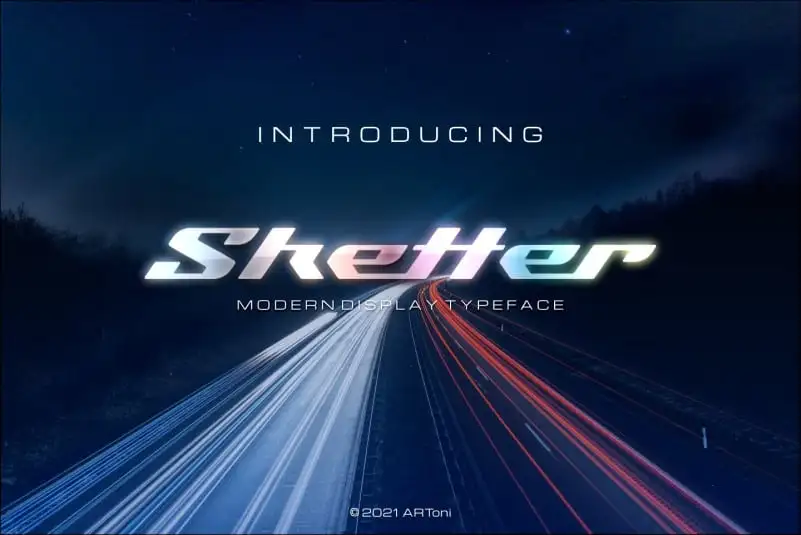
Sketter Display Font – Download Grátis
A fonte Sketter Display é uma excelente opção para projetistas que desejam criar designs chamativos e inovadores em plataformas digitais. Desenvolvida pela ARToni, ela se destaca por sua resolução de alta definição e formato vectorial, ideal para ambientes de exibição digital. A fonte traz um estilo único e duradouro, perfeito para aplicar em projetos relacionados a finanças e tecnologia. Se apaixone pelo seu design distintivo e clássico, pois ela será uma escolha inteligente para dar vida aos teus designs mais impressionantes e criativos.